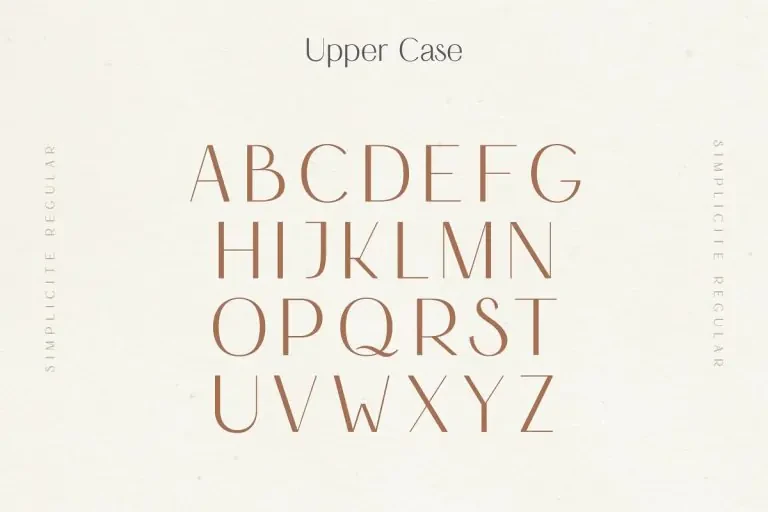
Simplicité Elegant Demo Font
Simplicité Elegant Free Font Harmonais Visual tarafından tasarlandı.
Simplicité Elegant Free Font, Harmonais Visual tarafından tasarlandı. Gösterim amacıyla kullanılan bir yazı tipi, güzel kontrastlara sahip. Alternatifler ve ligatür seçeneklerinin pek çokunu kullanmaktan memnun kalacaksınız; logolar, masthead veya başlıklar için mükemmel şekilde uygundur.